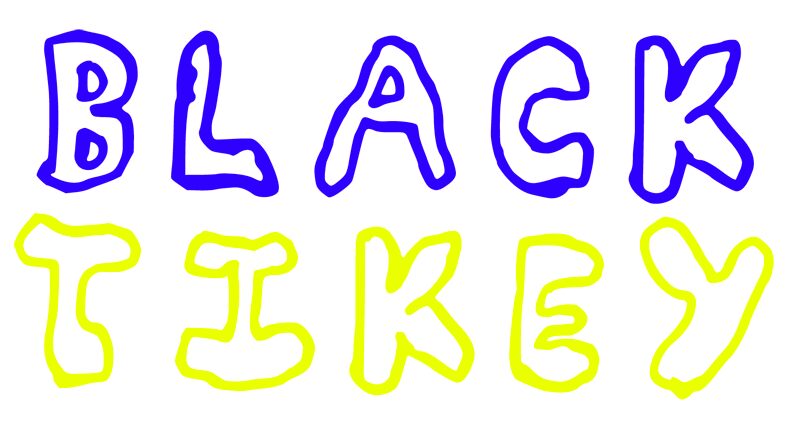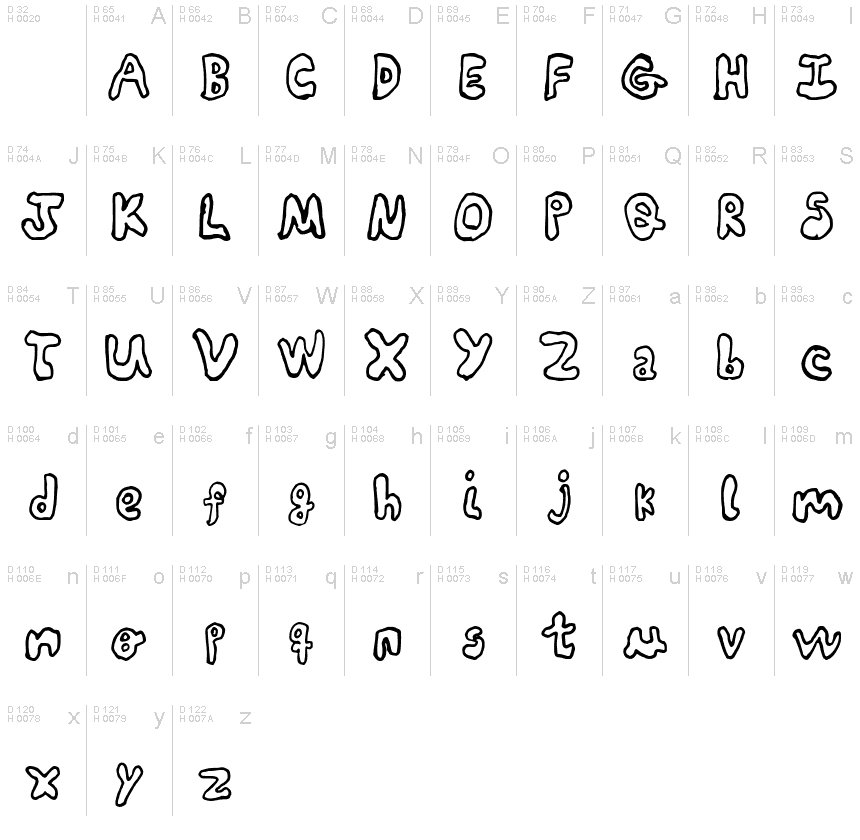
Blacktikey Regular
Criei essa fonte porque cansei de usar fontes de terceiros. Queria uma fonte que me permitisse monetiz-la sem que eu me preocupasse com questes ticas de direitos autorais, mas no estava achando. Ento resolvi faz-la.
I created this font because I got tired of using third party fonts. I wanted a text font that would allow me to monetize it without worrying about ethical copyright issues, but I didn't think so. So I decided to do it.